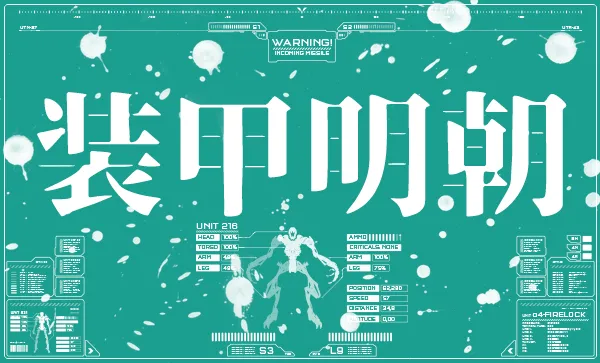
「裝甲明朝」看到這中文字體名稱是不是覺得很霸氣?如名稱一樣,字體風格硬朗有氣派,以及擁有軍隊級的氣氛、男人般涼意…… 若是拿來做越野車、大型裝甲機車等玩具淘寶海報設計就非常適用了。
這是一款免費使用的中文字體,由日本網友從開源字體「思源宋體」改版而來,基於SIL Open Font License 1.1協議,但最終出來的效果卻不大一樣,裝甲明朝體,將水平橫線筆劃修改得超細,在文字表現上,顯得張力更強,十分霸氣。
根據裝甲明朝開發者說明,這個字型適合使用於軍事或偏向陽剛的設計。